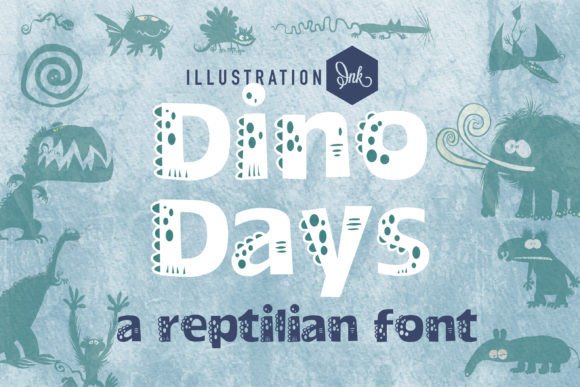
Dino Days
Trouver les bons éléments de conception peut être un défi, mais Dino Days propose une collection exceptionnelle qui rehausse instantanément votre travail.
Que vous créiez des produits POD (impression à la demande), des invitations de mariage ou des visuels pour les réseaux sociaux, Dino Days est un choix idéal.